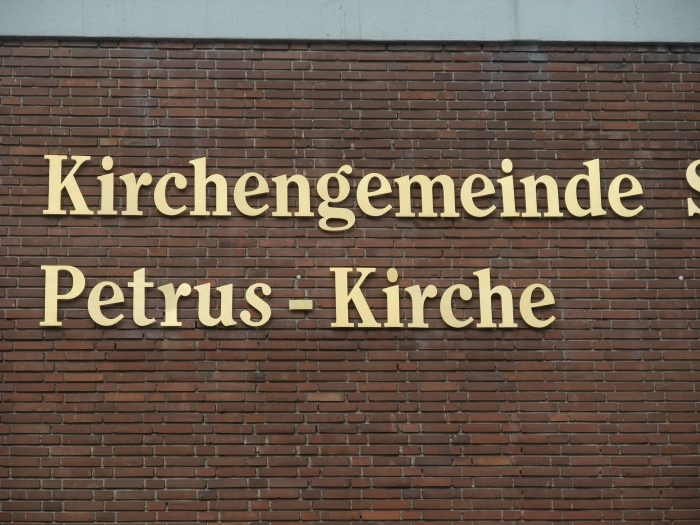
Schriftart unserer Kirchengemeinde mit Bild gesucht!
Ich soll für meine Kirchengemeinde einen Schriftzug erstellen, doch leider weiß keiner der Verantwortlichen mehr, um welche Schriftart es sich dabei handelt.
Ich habe mal ein entsprechendes Bild angehängt.
Hi chriboo,
mal ein Gedankenanstoß in eine andere Richtung: immer mehr Landeskirchen verfügen über ein recht anständiges Corporate Design. Vielleicht wäre es auch im Sinne des Einheitsgedankens, Eure Kirche in das entsprechende Erscheinungsbild einzugliedern und mit der empfohlenen Schriftart zu arbeiten.
dazu kann ich nicht viel sagen. Ich habe die Auflage, diese abgebildete Schriftart zu verwenden und daran halte ich mich, bloß weiß ich halt leider nicht, welche es ist.
Ich würde sagen, das ist eine ITC Clearface. Das leicht eingeschwungene r spricht dafür.
das scheint sie tatsächlich zu sein.
immer mehr Landeskirchen verfügen über ein recht anständiges Corporate Design. Vielleicht wäre es auch im Sinne des Einheitsgedankens, Eure Kirche in das entsprechende Erscheinungsbild einzugliedern und mit der empfohlenen Schriftart zu arbeiten.
Dass ich einen persönlichen Bezug zur Ortsgemeinde aufbaue, liegt (hoffentlich) sicher nicht an den Äußerlichkeiten, wie Architektur, Altarbild und Gestaltung der Fassade, sondern vielmehr an den lieb gewonnen Personen und damit entstanden Beziehungen, oder? Und natürlich den vielen Lebens-Höhepunkten, die man mit ihr verbindet …